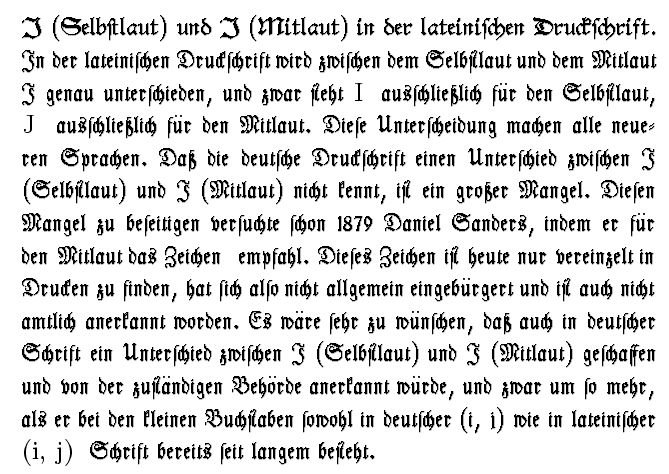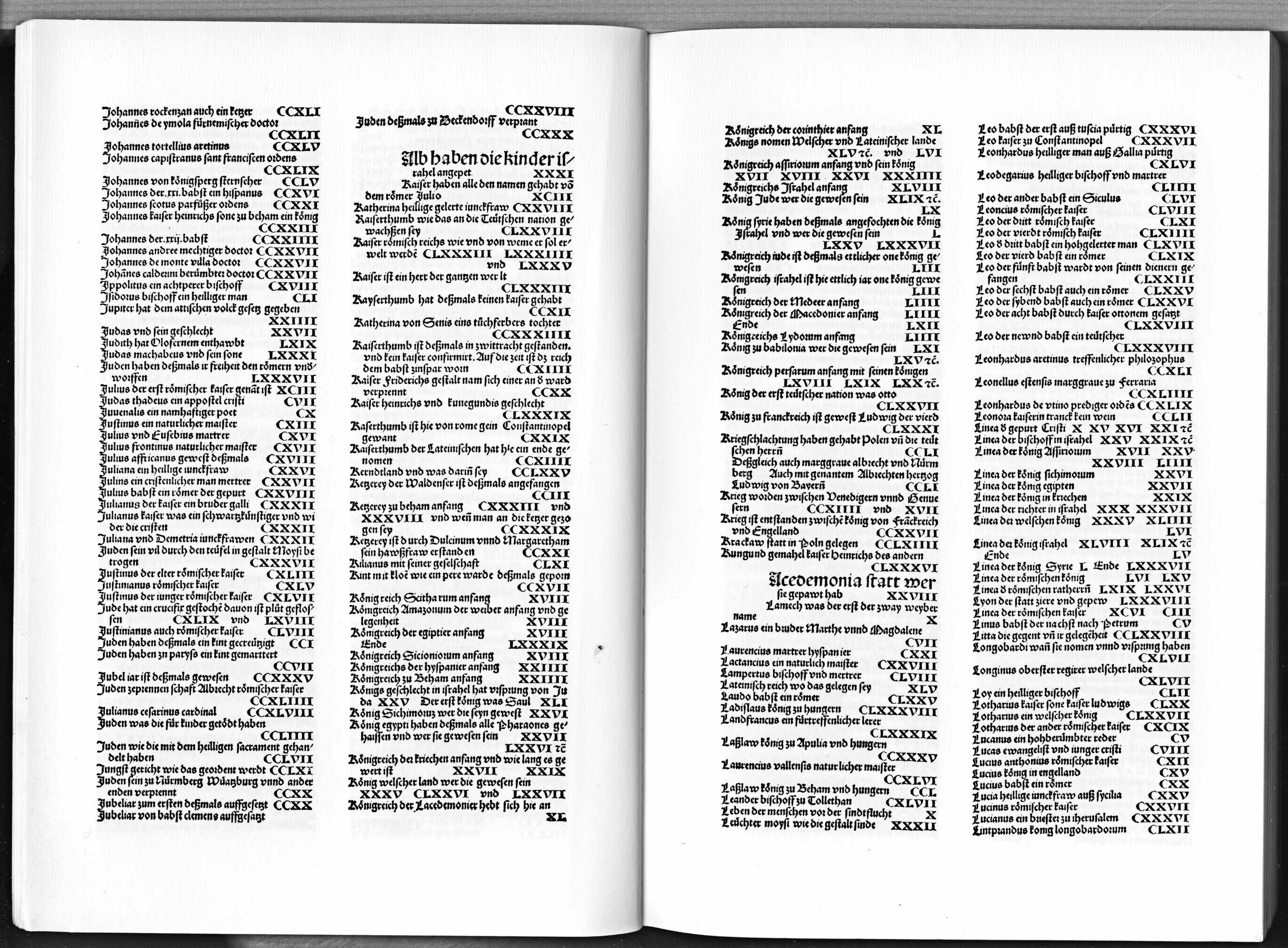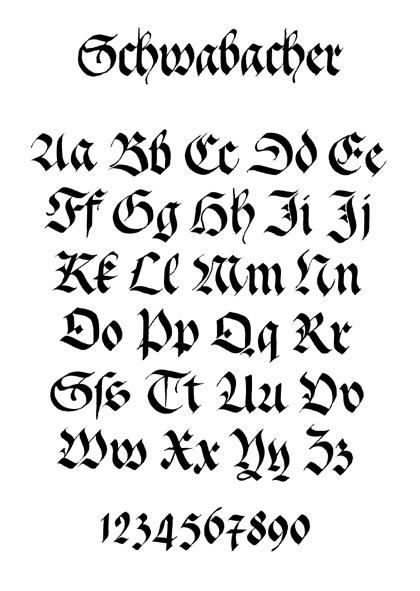
Schwabacher I und J.
Servus. Ich weiß nicht ob ich im Unterforum ‘Regeln’ richtig bin, aber ich versuche es mal: Bei der Schwabacher sind die Minuskeln ‘i’ und ‘j’ optisch unterscheidbar, die Majuskeln aber nicht. Nun muß ich mich bei der Transkription entscheiden ob ich versales ‘I’ oder ‘J’ tippe, was ist da historisch korrekt?
a) immer ‘I’
b) immer ‘J’
c) ‘I’ da wo als Minuskel ‘i’ erscheint/erschiene, und ‘J’ da wo als Minuskel ‘j’ erscheint/erschiene.
Hat jemand meine Frage gelesen?
Klar. Nur wird sich niemand eine Antwort aus dem Ärmel schütteln können.
Zunächst bin ich über die Aussage Bei der Schwabacher sind die Minuskeln ‘i’ und ‘j’ optisch unterscheidbar, die Majuskeln aber nicht gestolpert, weil es ja genügend Beispiele einer Schwabacher gibt, wo die versalen I und J durchaus unterschiedlich sind, beispielsweise hier:
Ich würde dann deine Version c) wählen, weil sie in meinen Augen als einzige korrekt ist. Warum sollte auch aus einem kleinen i ein großes J oder aus einem kleinen j ein großes I werden?
Nur nebenbei, weil es mich einfach interessiert und weil ich auf die Schnelle keinen Text in einer Schwabacher gefunden hab, der ein j oder J verwendet: Könntest du ein Beispiel zeigen?
Ich würde dann deine Version c) wählen, weil sie in meinen Augen als einzige korrekt ist. Warum sollte auch aus einem kleinen i ein großes J oder aus einem kleinen j ein großes I werden?
Ich glaube, Du hast die Frage falsch verstanden. Wenn ich es nicht falsch verstanden habe, geht es darum, wie der Originaltext [»Im Ianuar« bzw. »Jm Januar«] in moderner Antiqua wiederzugeben ist.
Was die eigentliche Frage betrifft, so würde ich behaupten, dass die Antwort von der Leserschaft und auch vom Kontext abhängt. Stehen Ortografie, Typografie o. Ä. im Vordergrund oder der Inhalt des Textes? Wie würdest Du in diesem Kontext ein langes s transkribieren?
@bertel M. E. sind diese unterschiedlichen Glyphen für versales I und J in der Schwabacher-Fonts entweder neueren Datums, jedenfalls nicht 17. Jh., oder gar eine Manipulation der Moderne. So lesen wir in Duden, Rechtschreibung der deutschen Sprache und der Fremdwörter. Leipzig Wien: Bibliographisches Institut, 1919:
Hier ein paar Eindrücke aus einem Druck von 1692, die Glyphen für versales I und J sind nicht ähnlich, sie sind genau gleich:
«Igel»
«In den»
«Indianiſche»
«Ja/ es iſt alſo»
«Jahren»
«Jungfraw»
Ich glaube, Du hast die Frage falsch verstanden. Wenn ich es nicht falsch verstanden habe, geht es darum, wie der Originaltext [»Im Ianuar« bzw. »Jm Januar«] in moderner Antiqua wiederzugeben ist.
Vielleicht hab ich das ;-) Wenn der Threadersteller aber davon ausgeht, dass I und J identisch aussehen, weiß er ja gar nicht, ob da »Im Ianuar« bzw. »Jm Januar« steht.
@Wrzlprmft Du hast die Frage richtig verstanden, und es geht – daher dieses Forum – nicht um Inhalt, sondern um Orthographie, Typogaphie :) Unser digitales Zeitalter erlaubt keinen “Zwischenzustand” zw. I und J. Eine Tastatur, Google, das Internet, kennt nur entweder oder. Wenn jemand in Google “Januar” sucht, wird er nicht “Ianuar” finden.
@bertel Zu deiner Frage, wie ich wissen kann, ob der Esel “Ja” oder “Ia” sagt, nun ja, die Wörter tauchen teilw. auch kleingeschrieben auf, teilw. hilft der Kontext, und teilw. bekommt man auch ein Gefühl dafür, wenn man viele Texte aus diesem Jahrhundert liest.
… Wenn jemand in Google “Januar” sucht, wird er nicht “Ianuar” finden.
Richtig. Nur hast du ja keine Google-Suche, sondern eine Transkription vor. Und da kommt es eben durchaus auf die damalige Schreibweise an, und die kann beispielsweise Ianuar sein. Daher auch Wrzlprmfts Frage, was denn im Vordergrund steht.
… teilw. hilft der Kontext, und teilw. bekommt man auch ein Gefühl dafür, wenn man viele Texte aus diesem Jahrhundert liest.
Hier eine Seite aus der Schedelschen Weltchronik, nicht Geringeres als das initiale Auftreten der Schwabacher. Was ist hier I? Was ist J? Sehen die beiden wirklich identisch aus?
Du hast die Frage richtig verstanden, und es geht – daher dieses Forum – nicht um Inhalt, sondern um Orthographie, Typogaphie :) Unser digitales Zeitalter erlaubt keinen “Zwischenzustand” zw. I und J. Eine Tastatur, Google, das Internet, kennt nur entweder oder. Wenn jemand in Google “Januar” sucht, wird er nicht “Ianuar” finden.
Hmm, der Mathematiker in mir würde in einem einleitenden Satz definieren, dass im Folgenden in Zitaten das Schwabacher-I/J mit J (oder I, Deine Wahl) wiedergegeben wird. Eine andere Möglichkeit wäre direkt in einer gebrochenen Schrift zu transkribieren oder Zeichen wie ℑ oder IJ zweckzuentfremden (mit vorheriger Erläuterung).
Ich meine eine einem Facsimile nahe kommende Transkription, kein Facsimile.
Wie gesagt: das gibt es nicht. Entweder willst du faksimilieren oder transkribieren. Abdruck oder Bedeutung.
Und je nachdem kommen J und I infrage. Die Erklärungen wurden ja ausführlich geliefert, unter anderem auch von dir selbst.
Eine dem Abdruck möglichst nahe kommende Bedeutungswiedergabe kann es aber nicht geben, da beide nun mal nicht kompatibel sind.
jede Schwabacher Letter ist einer lat. Letter 1:1 gleichzusetzen
Wenn dem so wäre, gäbe es dieses Strang ja nicht.